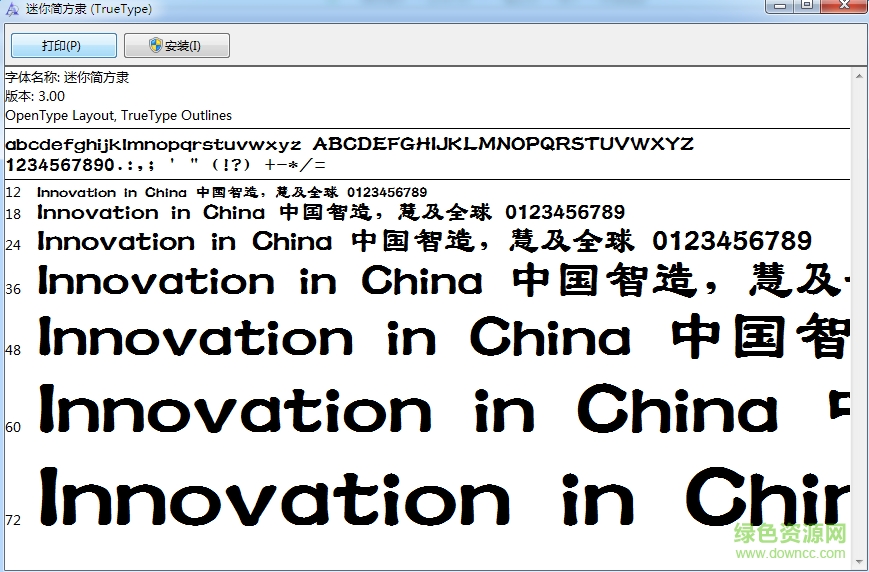
迷你簡(jiǎn)方隸是一款根據(jù)隸書(shū)制作的字體,字體結(jié)體扁平、工整、精巧,撇、捺、點(diǎn)等畫(huà)美化為向上挑起,輕重頓挫富有變化,具有書(shū)法藝術(shù)美,喜歡這款字體的朋友歡迎來(lái)綠色資源網(wǎng)下載體驗(yàn)!
迷你簡(jiǎn)方隸字體是一款具有古典美感的字體,看起來(lái)非常的大氣,就像是用毛筆寫(xiě)出來(lái)的一樣